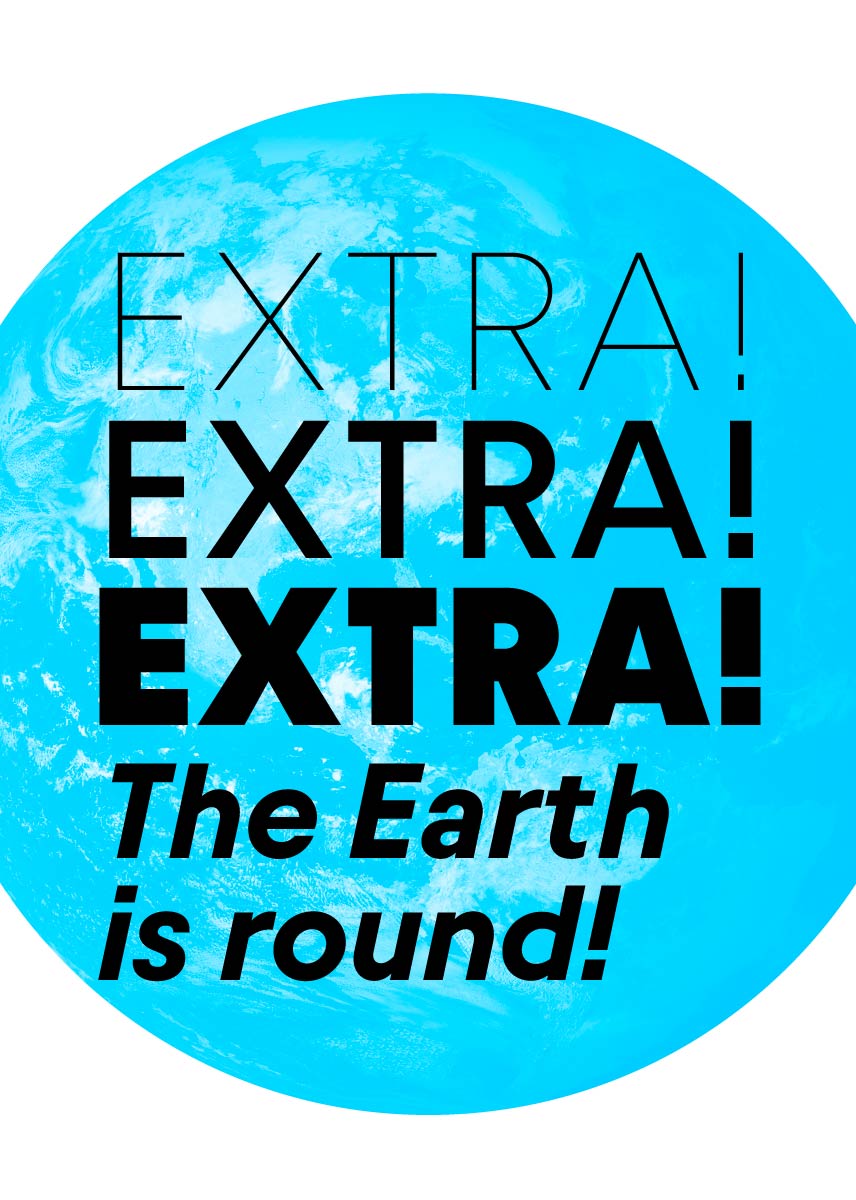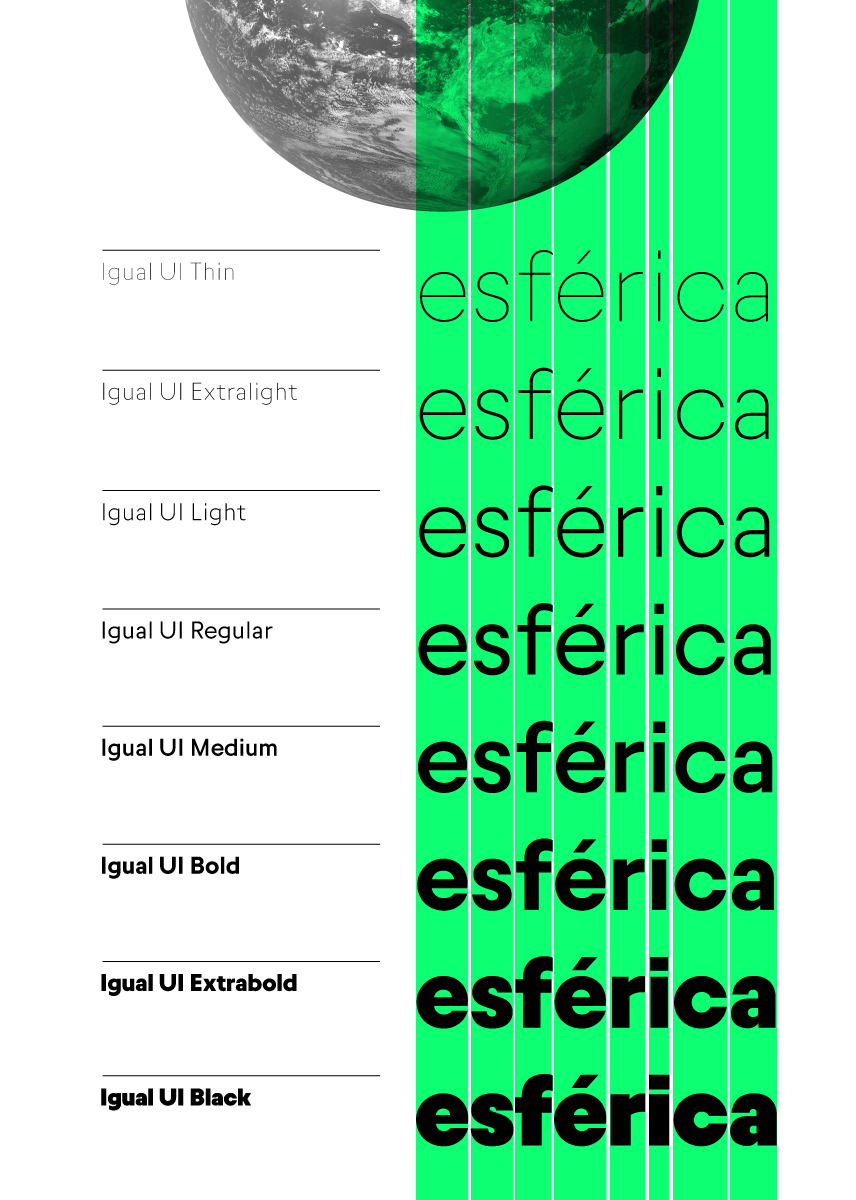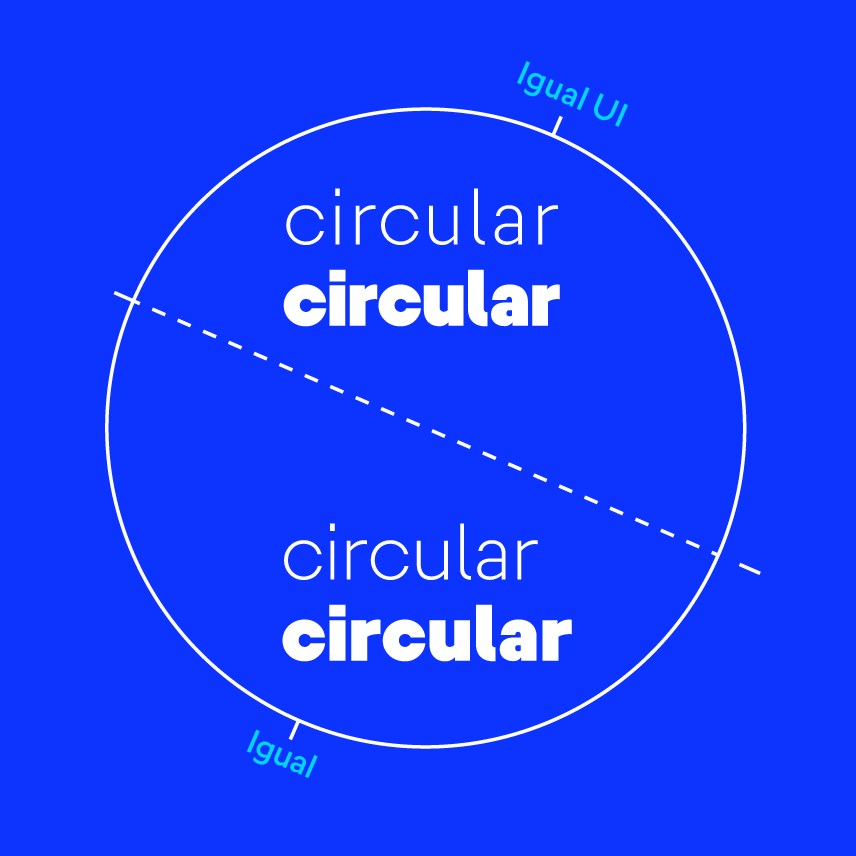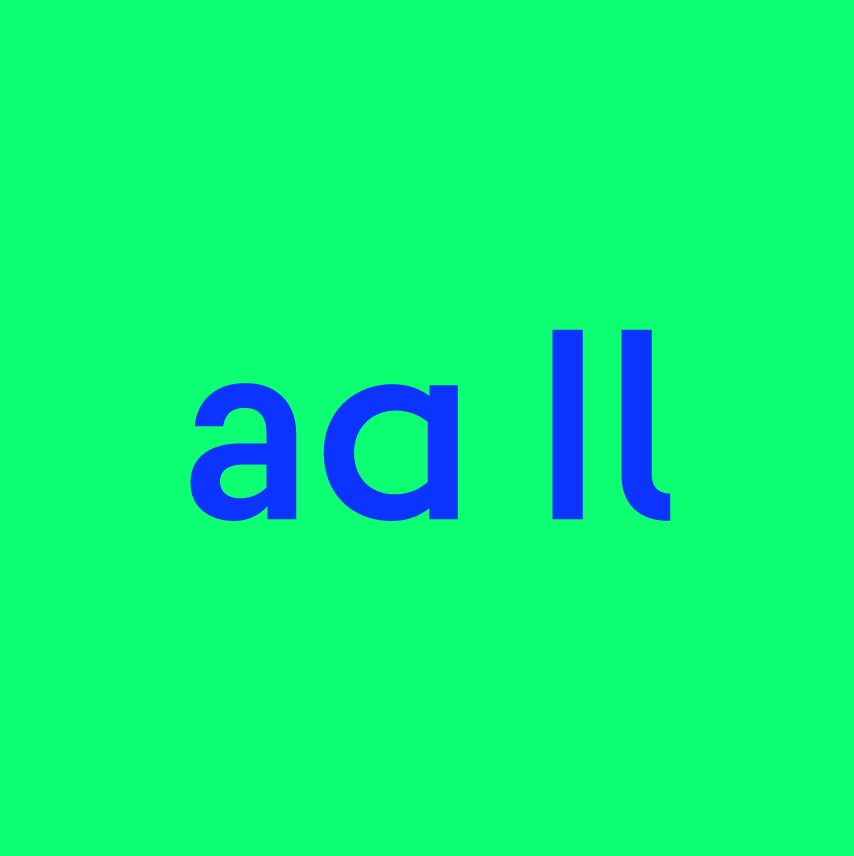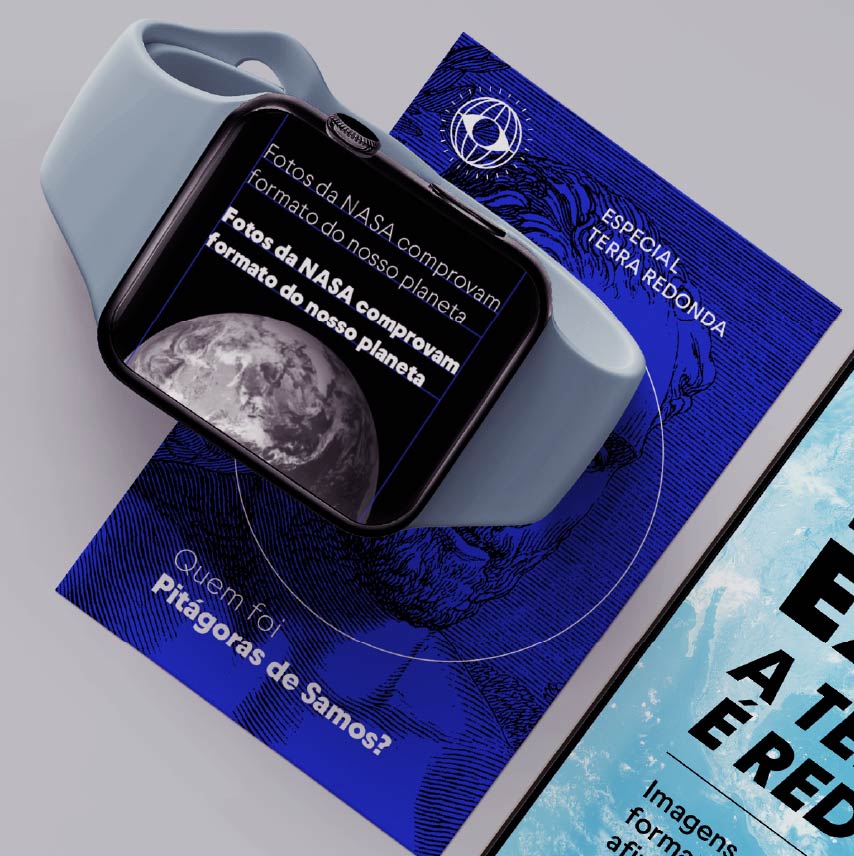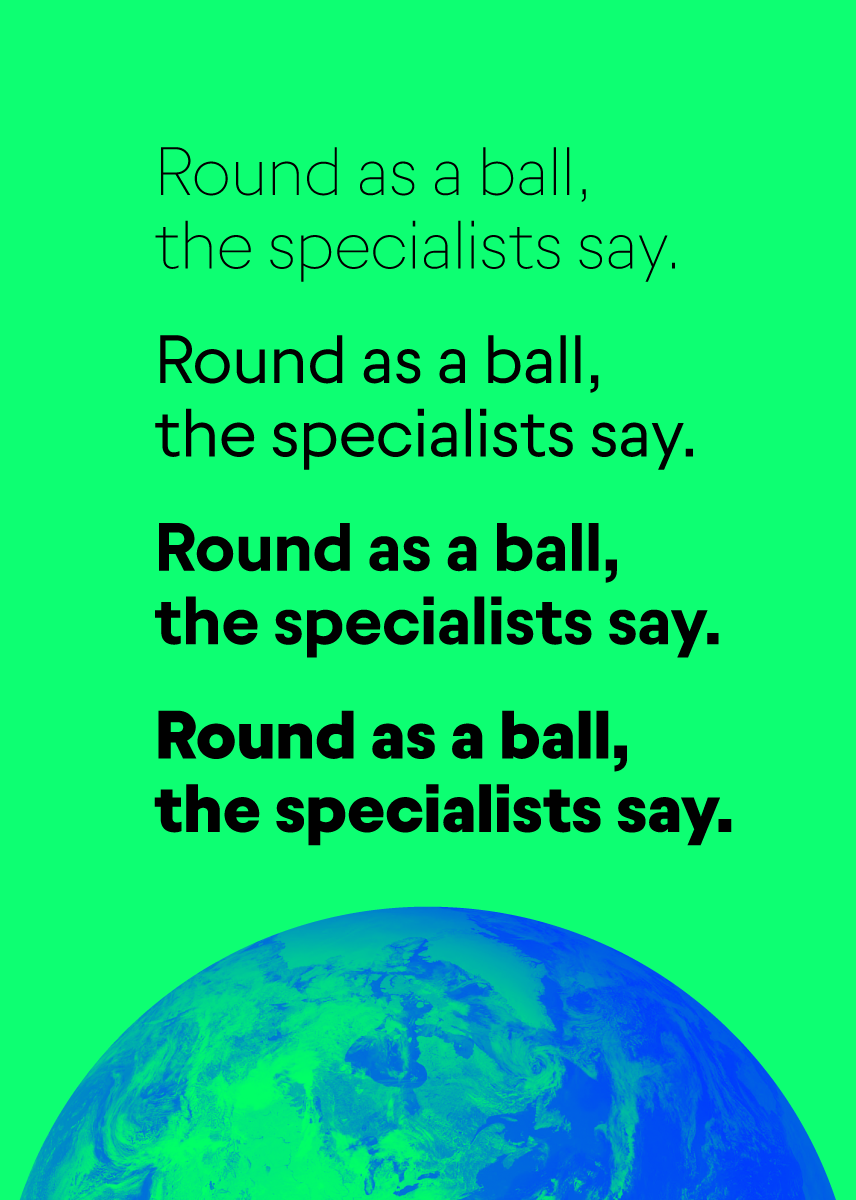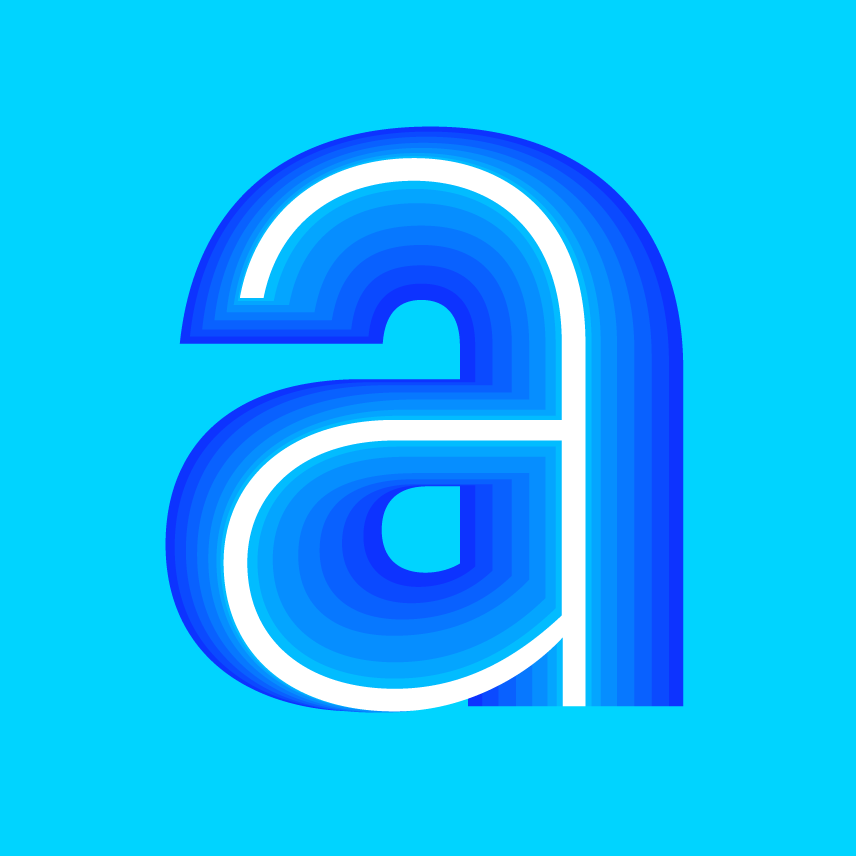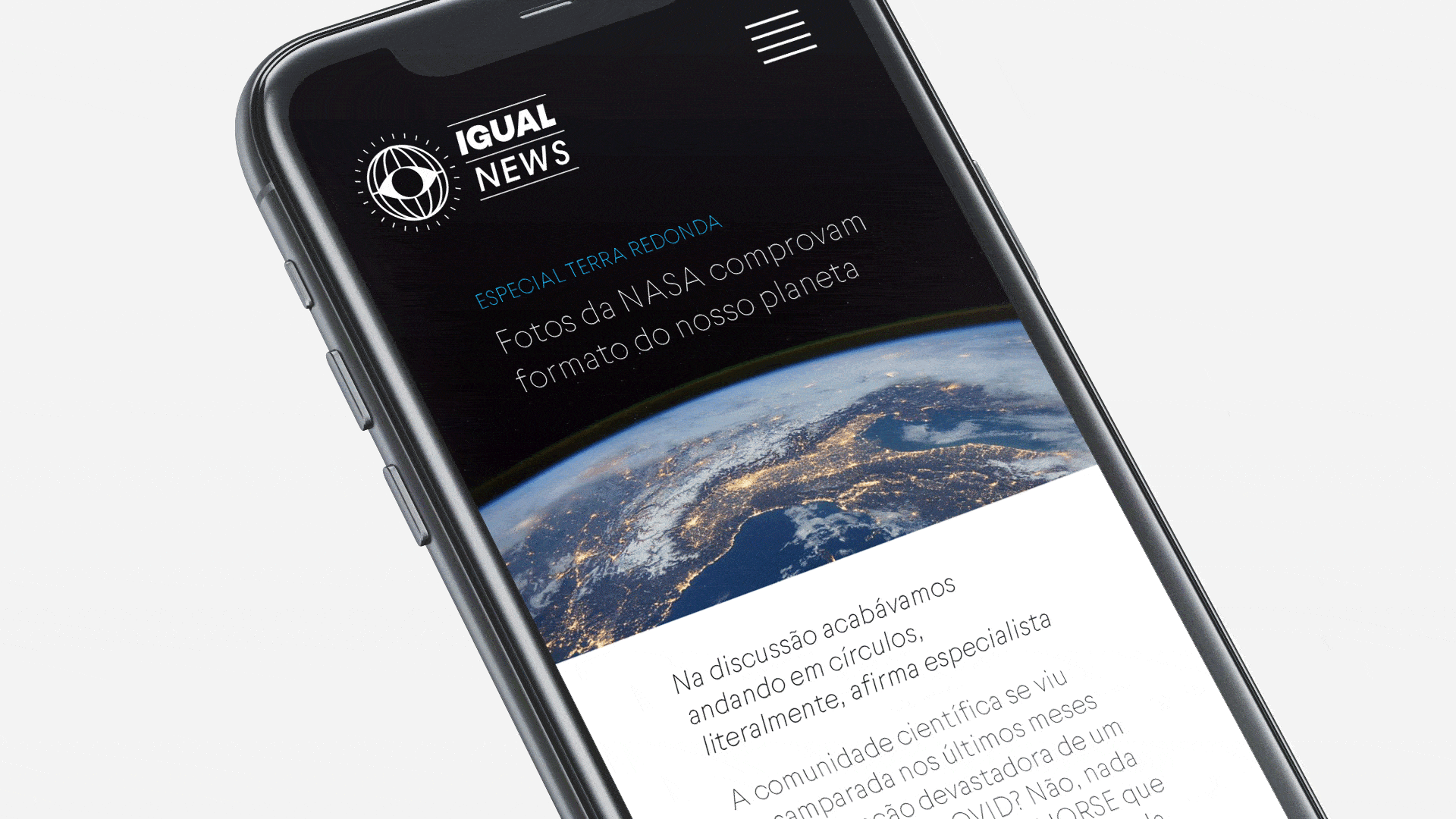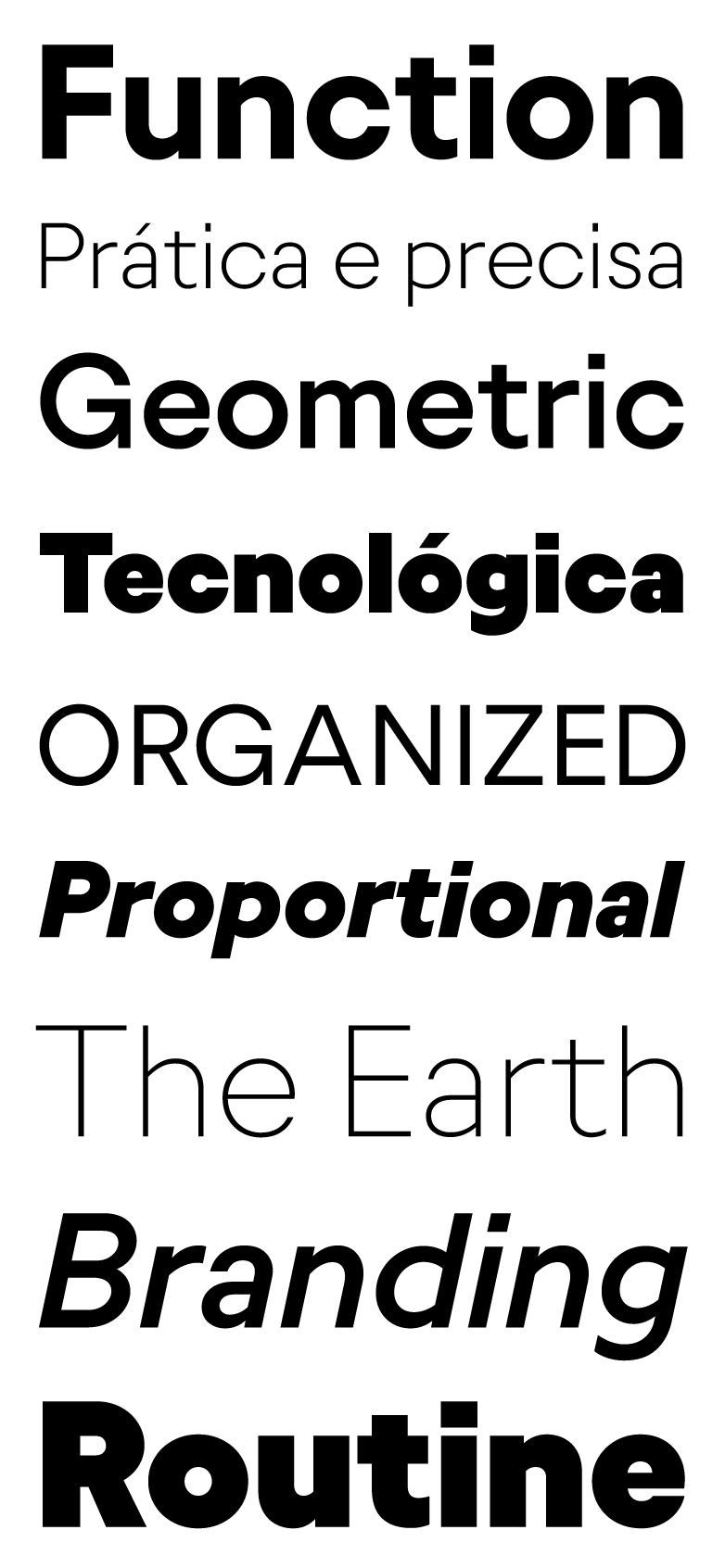
Se é um problema que os textos “corram” ao trocar de peso, a Igual está sempre na frente. Na versão UI, todos os pesos ocupam a mesma largura e são passíveis de ajustes com a tecnologia Variable Font (de acordo com o sensor de luminosidade de um celular, por exemplo) sem a alteração do layout da interface.
Apesar da estética de tipografias monospace (onde todos os caracteres têm a mesma largura), a Igual UI possui larguras diferentes entre as letras, mas não entre os pesos. Desta forma, a legibilidade das letras largas, como “m” ou “w”, não é sacrificada.
Já a versão padrão tem larguras variadas, ideais para uso em branding e na comunicação em geral, mas sempre com sua estética mecânica, precisa e racional.